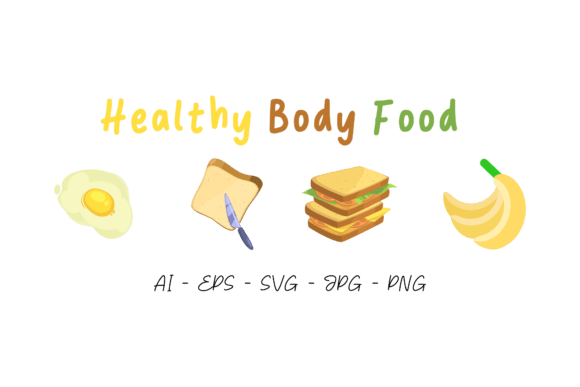
Healthy Body Food
หากคุณกำลังมองหาเนื้อหาคุณภาพสูงเช่น Healthy Body Food แพ็คเกจพรีเมียมนี้เป็นตัวเลือกที่ยอดเยี่ยมสำหรับโปรเจ็กต์สร้างสรรค์ของคุณ
สร้างขึ้นอย่างแม่นยำ Healthy Body Food ให้เวกเตอร์ที่สะอาด พิมพ์ตัวอักษรที่ราบรื่น และใบอนุญาตเชิงพาณิชย์เพื่อความสบายใจ
ไม่ว่าคุณจะสร้างผลิตภัณฑ์ POD (Print on Demand) คำเชิญงานแต่งงาน หรือกราฟิกโซเชียลมีเดีย Healthy Body Food ก็เหมาะสมอย่างยิ่ง